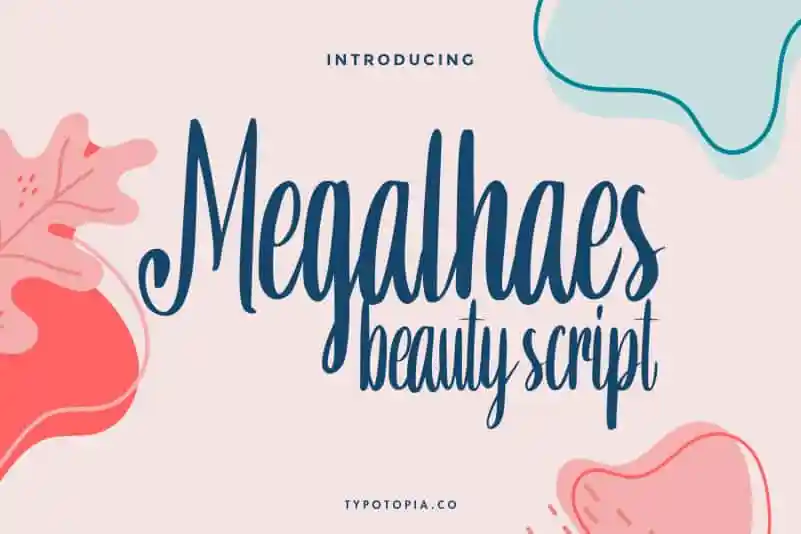
Megalhaes Beauty Script Font – Download Grátis
A fonte ‘Megalhaes Beauty Script Font’ é uma criação única e extravagante do designer typotopia, perfeita para quem busca desenhar design elegante e sofisticado. Com sua natureza brilhante e surpreendente, esta fonte pode ser usada em um vasto número de projetos gráficos, desde logomarcas até embalagens, aplicações e selos personalizados. Ela é perfeitamente adequada para projetos onde você deseja transmitir uma mensagem pessoal ou exibir elegância. Essencialmente, ela é uma fonte que combina características do script com elementos extravagantes de maneira única. Seja para criar um design inovador para um logotipo, personalizar mensagens impressas, enviar convites de evento ou até mesmo desenhar etiquetas e embalagens, esta fonte oferece a oportunidade de transformar seus projetos em verdadeiras obras de arte. Se você está buscando uma font que expressa sua personalidade através do design gráfico, ‘Megalhaes Beauty Script Font’ é definitivamente uma opção que vale cada centavo.